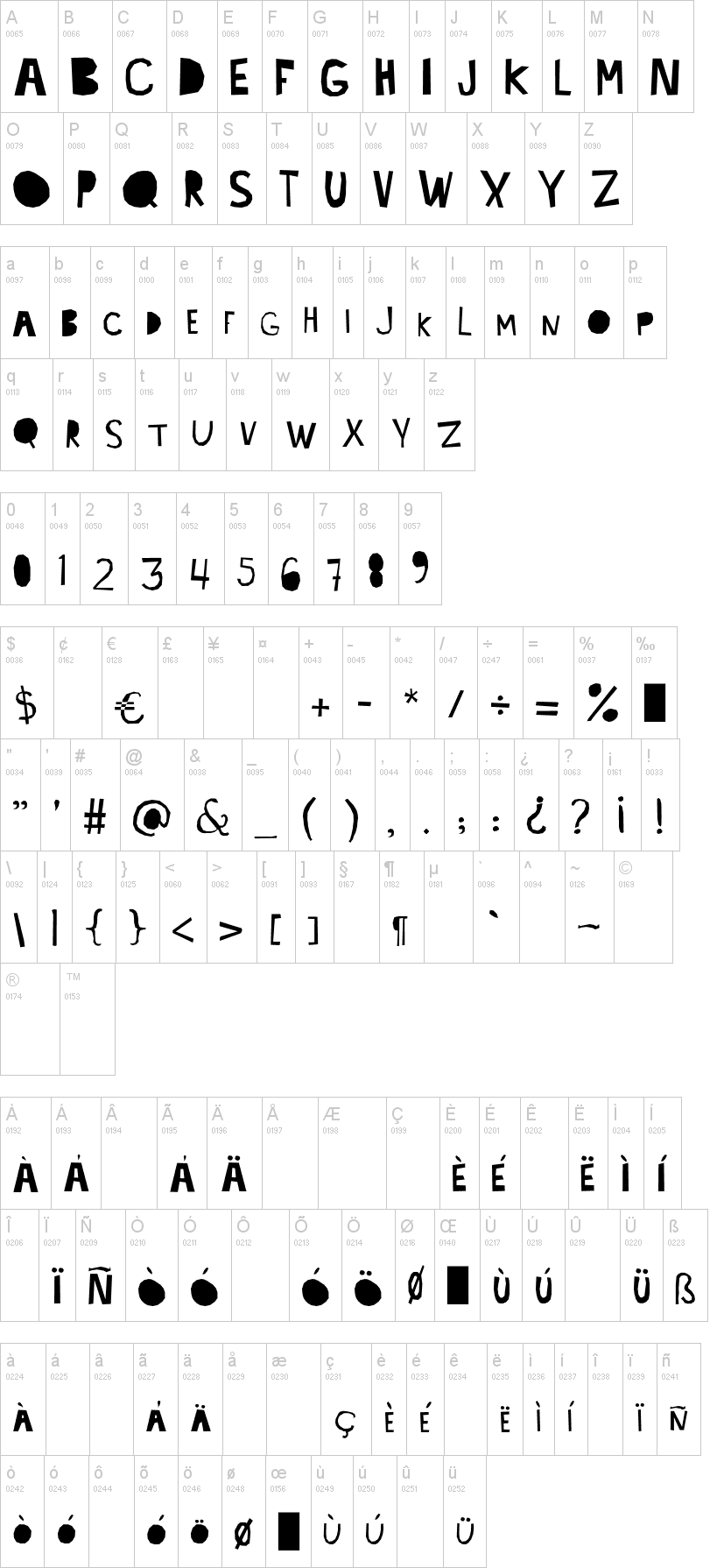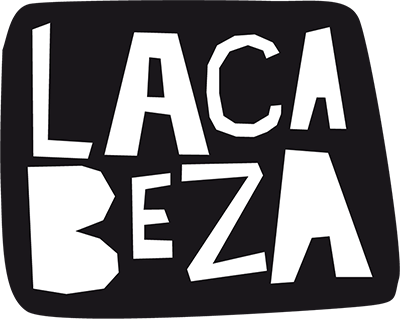
Шрифт Lacabeza
LACABEZA
La tipo LACABEZA es una tipo que he diseñado para la revista que he creado : LACABEZA, por eso me gustaría pedirles que contribuyeran con su aporte (si al final van a utilizarla para su trabajo).
LACABEZA typo is a font I designed for the magazine I created : LACABEZA, thats why Id like to ask you to collaborate with a small contribution (if you eventually use my typo for your work).